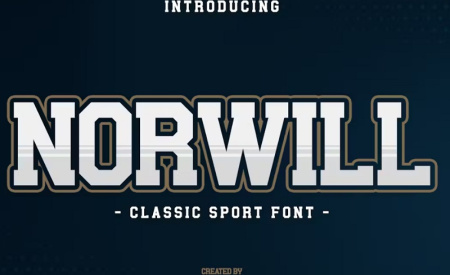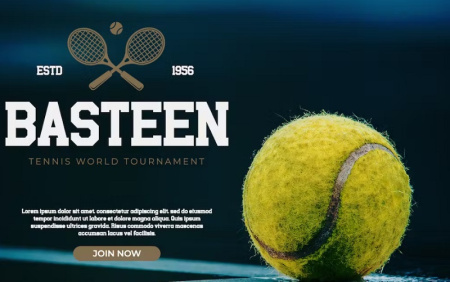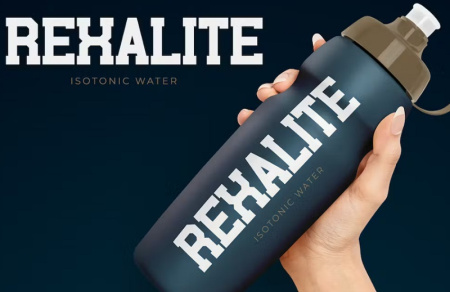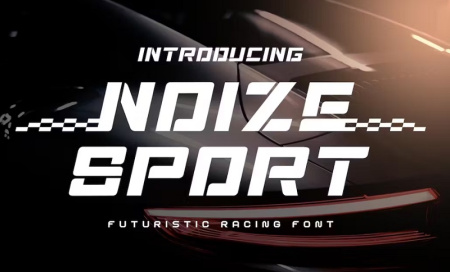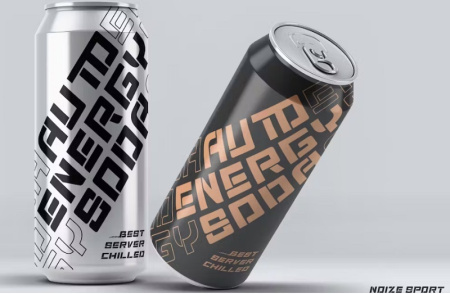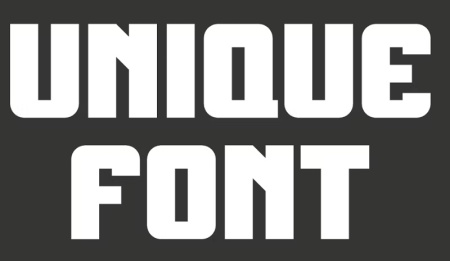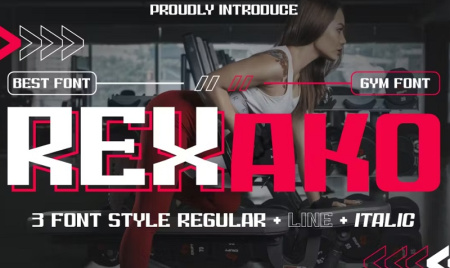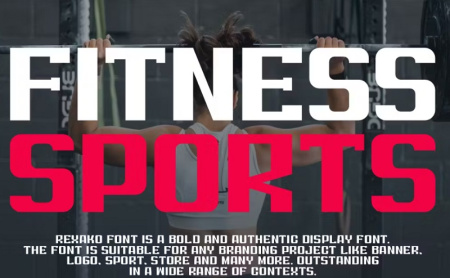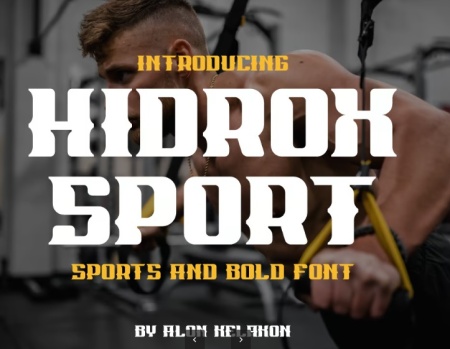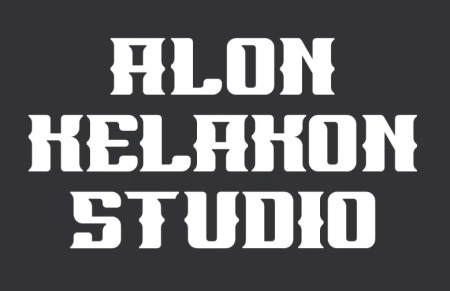
6 فونت انگلیسی ورزشی Sporter
فونت انگلیسی ورزشی
فونت انگلیسی ورزشی از جی اف ایکس دانلود. این مجموعه برای تم ورزشی و اسپرت ارائه شده است. فونت ورزشی انگلیسی مناسب برای تیتر، لوگوتایپ، پوشاک، دعوت نامه، برندسازی، بسته بندی، تبلیغات و غیره با مضمون قدیمی و همچنین مدرن می باشد. می توانید از این فونت های انگلیسی ورزشی جذاب برای طراحی پوستر های ورزشی، طراحی های گرافیکی و ... استفاده کنید. برای مشاهده پیش نمایش این فونت ها در ادامه از جی اف ایکس دانلود با ما همراه باشید.
Rexako نام این فونت انگلیسی ورزشی و اسپرت می باشد که برای هر پروژه برندسازی مانند لوگو، ورزش و بسیاری موارد دیگر مناسب است. از این فونت زیبا می‌توانید برای طراحی‌های تبلیغاتی و گرافیکی مربوط به ورزش، تیم‌های ورزشی، لوگو و ... استفاده کنید.
فونت انگلیسی با سبک ورزشی و اسپرت
Aerob Sport نام این فونت انگلیسی ورزشی و اسپرت است که برای انواع پروژه های طراحی، از جمله لوگو و برند تجاری، پست های رسانه های اجتماعی، تبلیغات و طرح های محصول مناسب می باشد.
✅ نام فونت انگلیسی 1: Norwill-Sport
✅ نام فونت انگلیسی 2: Noize Sport
✅ نام فونت انگلیسی 3: Sporter
✅ نام فونت انگلیسی 4: Rexako
✅ نام فونت انگلیسی 5: Hydrox Sport
✅ نام فونت انگلیسی 6: Aerob Sport - Techno Sport